8. Formas – Animación
8.1 Distorsión
La tipografía puede distorsionarse de múltiples formas y la mayoría de los programas informáticos de animación proporcionan un acceso fácil a filtros y herramientas que permiten aplicar toda una serie de efectos visuales.
Depende del software que usen para animar, será la gama de efectos de distorsión que pueden implementar, aquí algunos comunes.
(Desenfoque, fractura, checar otros 3 o 5 en after effects)
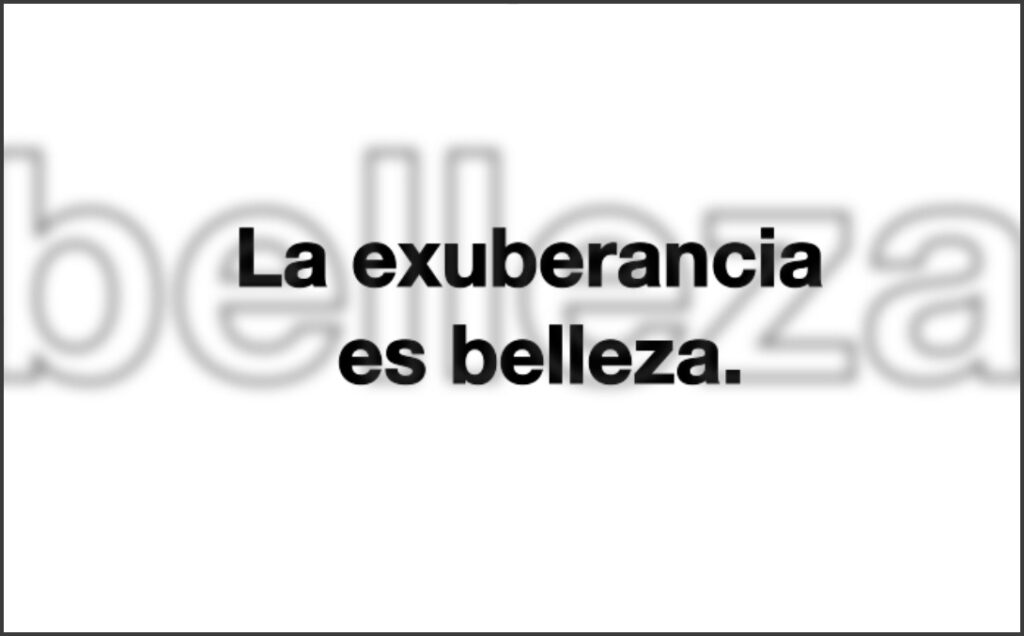
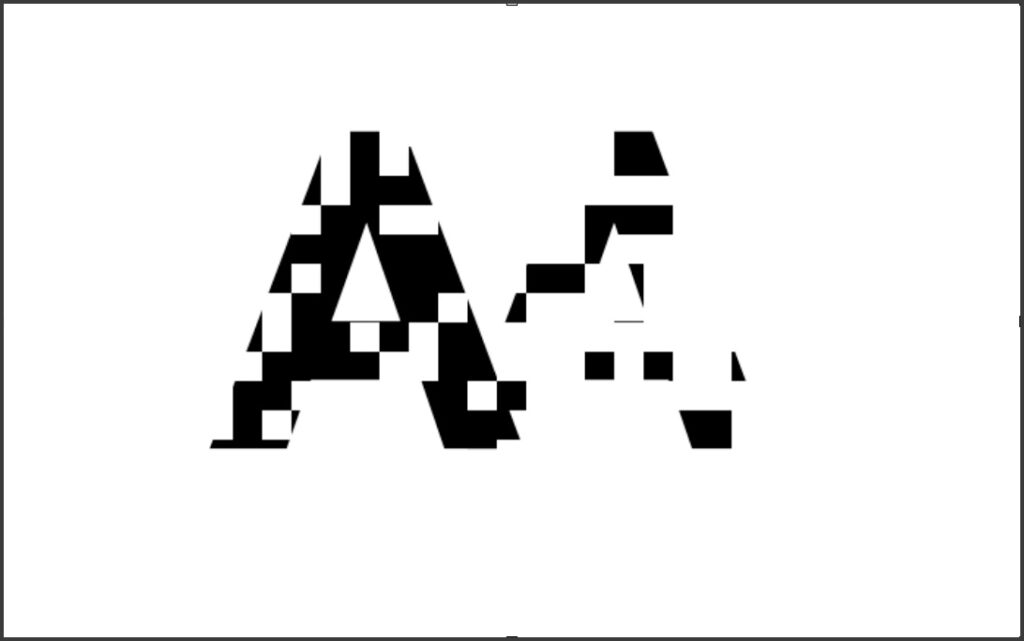
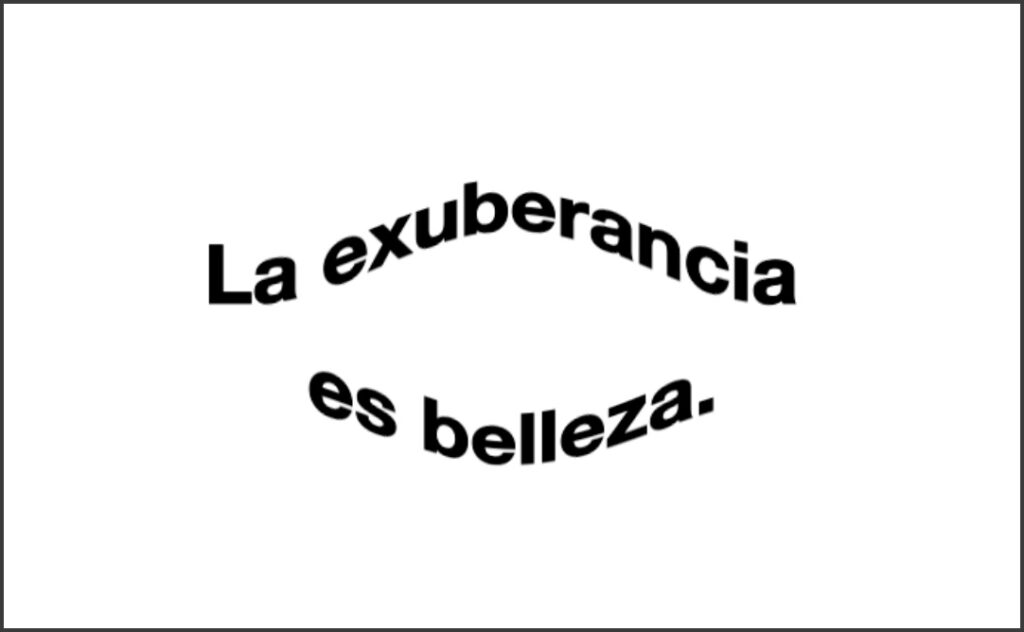
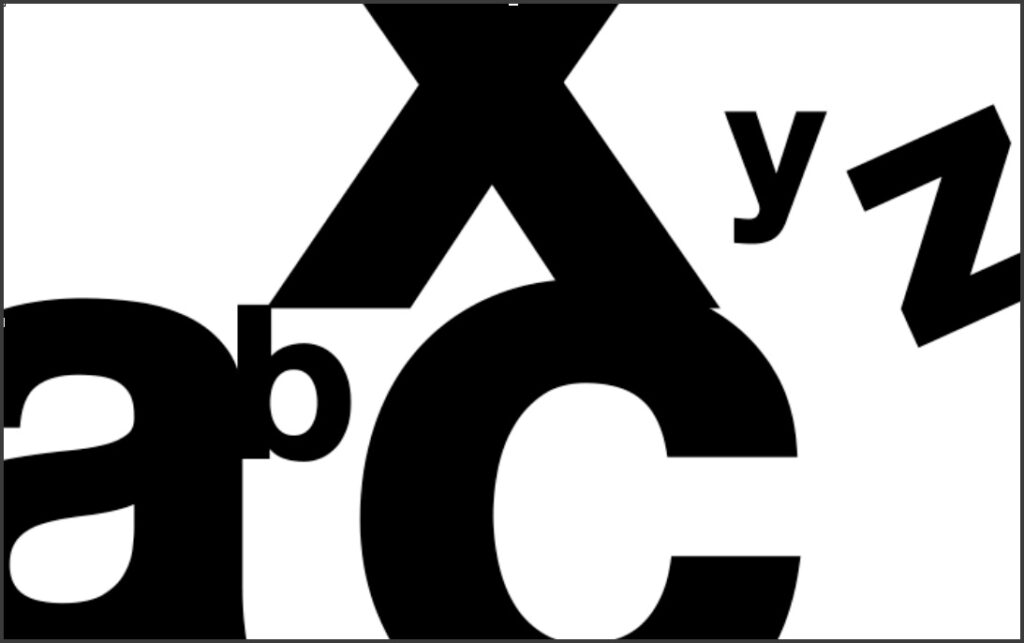
Elaboración
La elaboración de las letras y palabras puede ser un eficaz método para crear un énfasis o jerarquía visual.
Algunos ejemplos de elaboración de énfasis o jerarquía visual
(Color, adición, negación, destacado, substracción, repetición y extensión.)
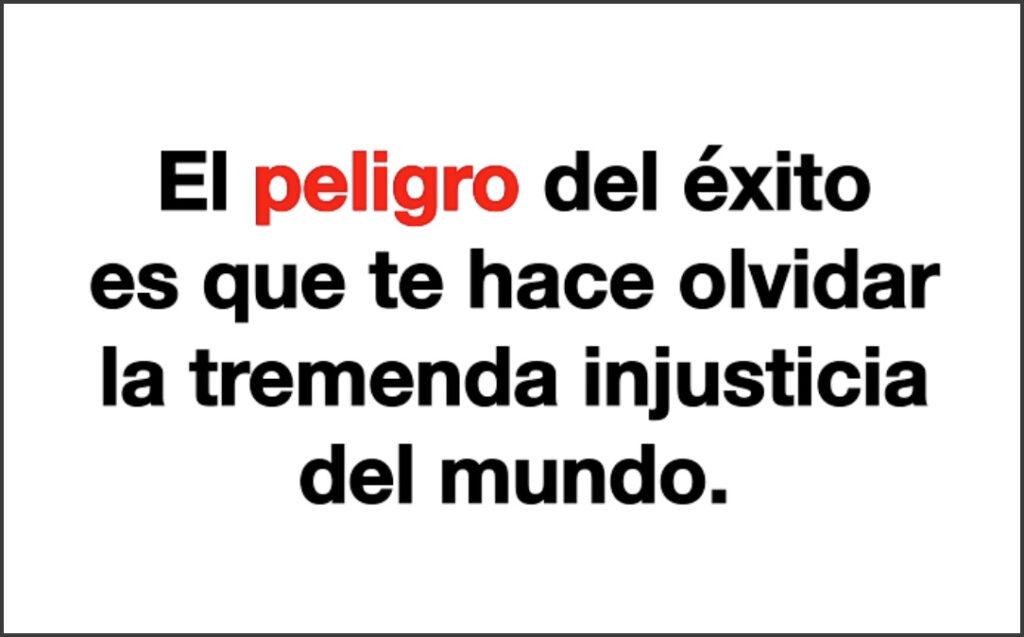
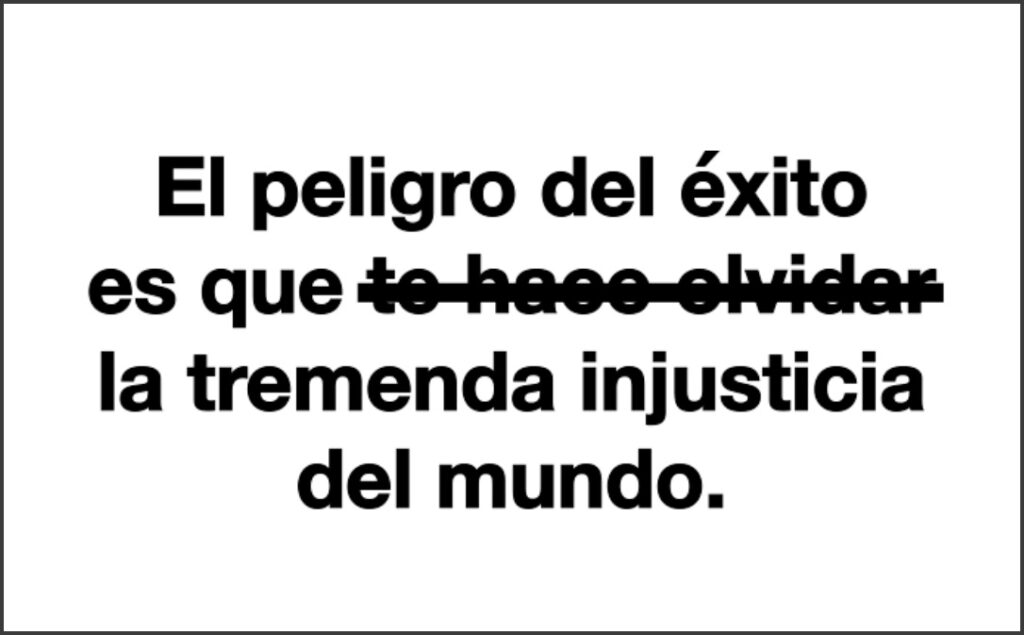
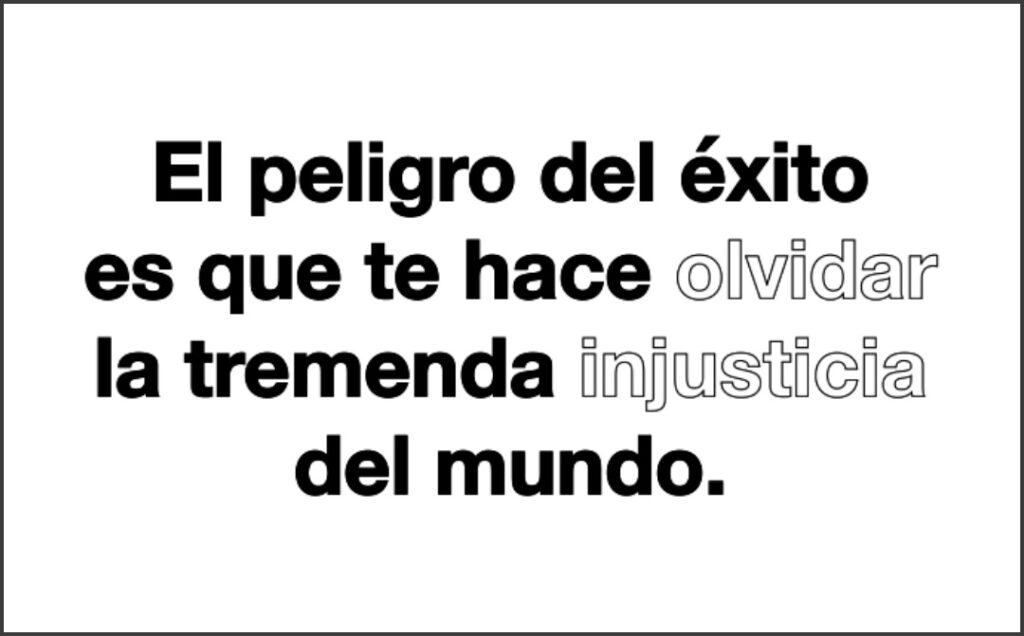
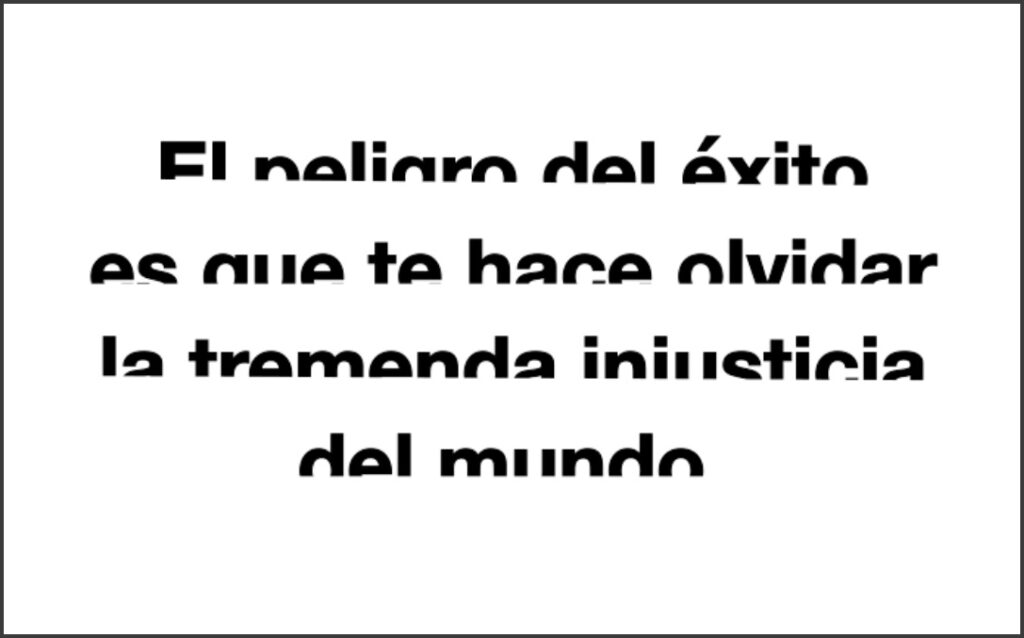
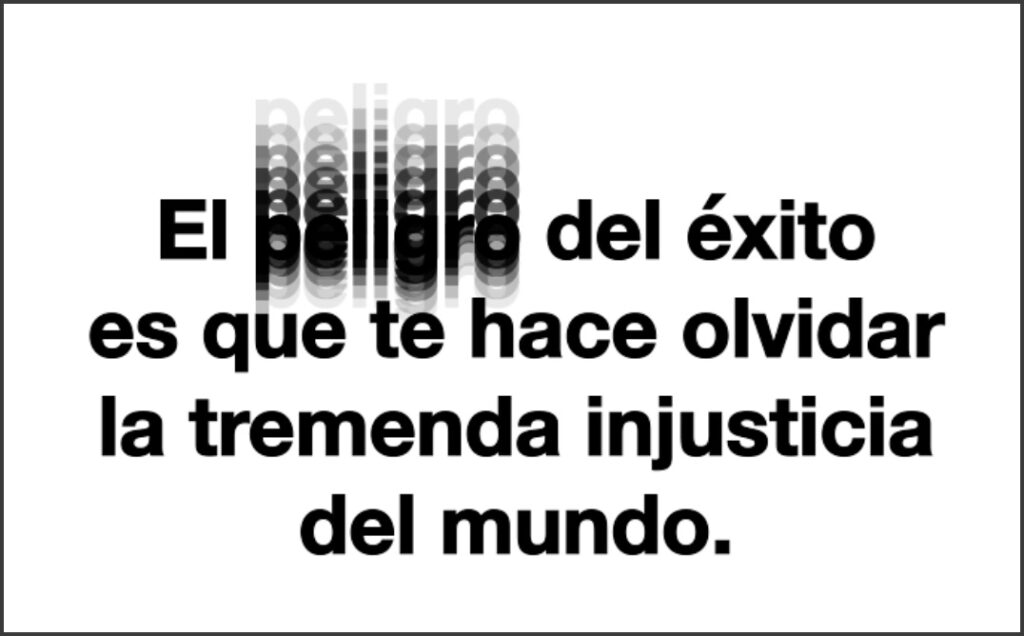
Dimensionalidad
Aquí nos referimos en darle una simulación de superficie a las letras, puede ser con sombras, texturas y efectos 3D.